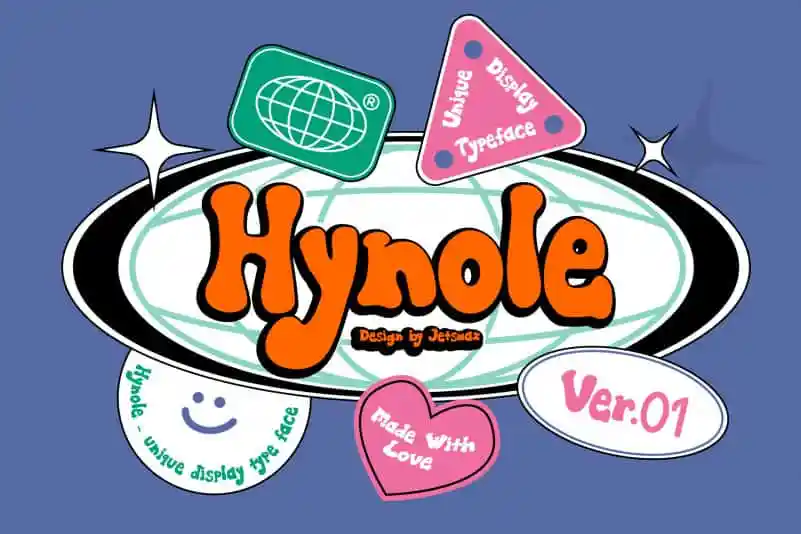
Hynole Display Font – Download Grátis
A Hynole Display Font é uma escolha perfeita para projetos que exigem estilo brilhante e versão moderna do tipo retro dos anos 80. Inspirada no design alegre e vibrante dos anos 80, essa fonte oferece um equilíbrio entre elegância e destaque, permitindo que seus projetos de design se destacuem. Seja você criando um layout editorial, um logotipo em alta resolução ou um design gráfico impactante para uma campanha publicitária, a Hynole Display Font fornecerá o toque final sofisticado e moderno que seu projeto merece. Ideal tanto para designers profissionais quanto para iniciantes, esta fonte é certamente um investimento inteligente para qualquer criativo em busca de uma maneira única de destacar seus designs no mercado atual.